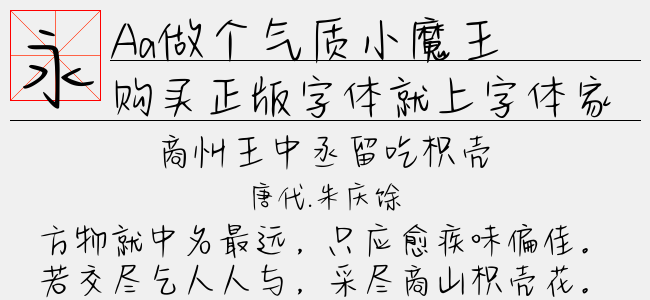
Aa做个气质小魔王 字体大小4.99 M,包含了6763个汉字以及附加其他英文字体和阿拉伯数字,属于Aa字体。Aa做个气质小魔王(TTF)可以免费下载,商业用途请自行购买版权,它的特征就是手写,个性,卡通,海报,采用安装嵌入的安装方式,支持符号拉丁文日文中文等语言
字体作者:Aa字体
字体名称:Aa做个气质小魔王